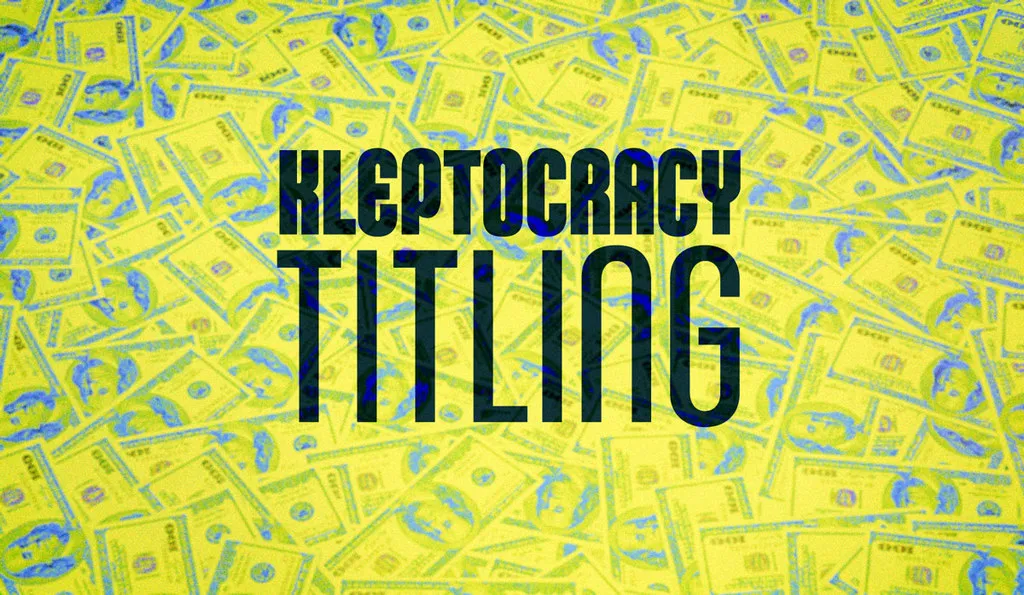
A fonte Kleptocracy é uma escolha interessante para designers que buscam um equilíbrio entre eficiência industrial e elegância suave. Esta fonte, especialmente sua versão com letras em maiúsculas apenas, oferece um contraste atraente: perfeita praquedoção onde outras fontes criadas na linha de montagem soam ruidosas. A Kleptocracy é uma criação da typodermicfonts, um local de referência confiável no ramo dos materiais gráficos. Com formas arredondadas suavemente misturadas às linhas retas e perfeitas, a Kleptocracy oferece não apenas estilo, mas também uma sensação sofisticada que pode se destacar em qualquer projeto visual. Ainda mais interessante é o fato de ser uma opção gratuita, tornando-a ainda mais acessível para designers independentes ou estudantes procurando por recursos gráficos excelentes.